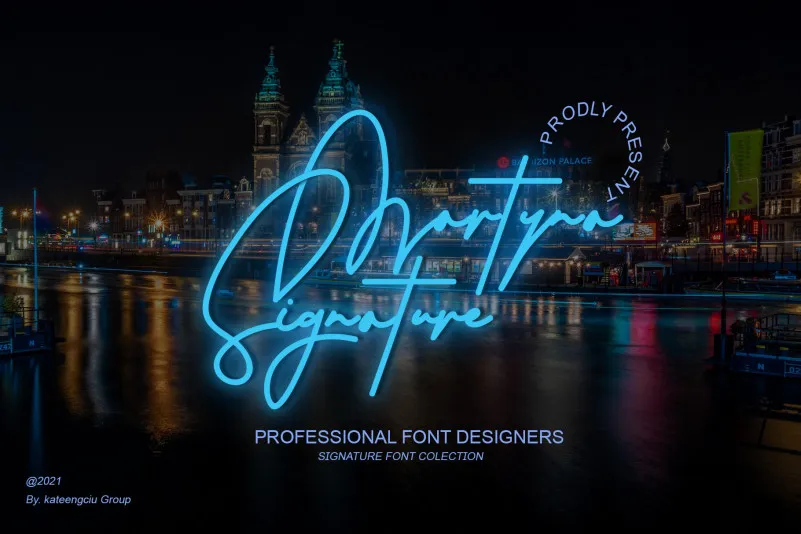
Martyna Signature Font – Download Grátis
Esta é uma fonte escrita a mão suave que se destaca tanto para projetos simples quanto complexos. Ela tem uma textura quirk e jolly, sendo perfeita para transformar as suas ideias em obras de arte únicas. Com este belo estilo, você pode explorar sem restrição seus infindáveis variâncias. A Kateengciu nos oferece a opção de adicionar um toque pessoal aos seus projetos com essa fonte escrita a mão, tornando cada trabalho mais personalizado e encantador. Experimente as diferentes formas e tamanhos desta fonte e descubra como ela pode transformar seu design em algo único e quase realista. É uma ótima escolha para aqueles que buscam um toque autêntico em suas criações digitais, seja você criando materiais gráficos ou desenvolvendo layouts. Experimente a Kateengciu Martyna Signature Font e descubra o verdadeiro potencial da escrita a mão digital.